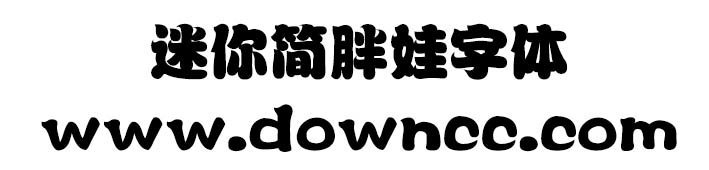
迷你簡(jiǎn)胖娃字體是一款比較圓潤(rùn)的電腦字體軟件,非常適用于平常的簡(jiǎn)單設(shè)計(jì)中使用,使用流暢字體酷炫,定能滿(mǎn)足你在生活中的字體需求??靵?lái)綠色資源網(wǎng)下載體驗(yàn)吧!
迷你簡(jiǎn)胖娃是迷你簡(jiǎn)字體的一種,這個(gè)字體看著圓咕隆咚,界面非常美觀。字體設(shè)計(jì)大方端正,但不是很工整,可以應(yīng)用于兒童繪畫(huà),藝術(shù)設(shè)計(jì),廣告平面設(shè)計(jì)、正文標(biāo)題等人員使用。有喜歡的朋友可以下載使用。